ADCグランプリ「INDUSTRIAL JP」のフォント
約8000点の応募作品の中から、ADC(東京アートディレクターズクラブ)による2017年のADCグランプリを獲得したのは、町工場6社による「INDUSTRIAL JP」のWebサイトと映像でした。そのWebサイトのアートディレクションからデザイン、フロントエンドエンジニアリングまでのすべてを担当したのは、DELTRO INC.(デルトロ)のアートディレクター/デザイナーの坂本政則氏と、テクニカルディレクター/プログラマーの村山健氏です。 デルトロは、坂本政則氏と村山健氏が2009年に設立したデザインファームで、Webサイトやアプリケーション、デジタルサイネージなどのオンスクリーン・メディア、グラフィックデザインやインスタレーションなど、主に広告プロジェクト分野で活躍しています。
「INDUSTRIAL JP」は、町工場の音楽レーベル化として発信することを目的として、町工場の製造現場で採取した機械音をサンプリングし、ミュージシャンがオリジナル楽曲を作成しています。また、製造工程を撮影した動画とミックスすることでミュージックビデオも制作しています。
そして、「INDUSTRIAL JP」のWebサイトでは、AXIS Fontコンデンスが使われています。 このプロジェクトは、「町工場や中小企業のために、クリエイティブの力でできることは何か」という、町工場の社長と電通のクリエイティブディレクターとの議論から始まりました。「INDUSTRIAL JP」は、その議論に対し、アートディレクター/グラフィックデザイナーである、下浜臨太郎氏が発案したプロジェクトで、サウンドディレクターの木村年秀氏(MOODMAN)を含めたメンバーが主体となり、全体のプランニングや映像のディレクションおよびマネージメントなどが行われました。
坂本氏は、「デルトロでは、Webサイトのプランニング、アートディレクション、デザイン、フロントエンドエンジニアリングに関してのお手伝いをしています。『INDUSTRIAL JP』のミュージックビデオは、工作機械が反復するアルゴリズムと、同じく一定のリズムを刻むテクノサウンドにより成り立っています。Webサイトでは、その質感とそれらの背景にある、工業機器、電子回路図、DAWソフトウェア、フィジカルコントローラーなどの要素を融合させた質感を目指し、アートディレクション、デザインを行いました」と述べています。
坂本氏は高校時代に、機械設計(CAD)や溶接、プログラミングといった一連の機械技術を学びました。書体選定においては、その当時に毎日のように見ていた、CADフォントや製図用テンプレート文字、金属板打刻文字などを想起させる印象を持つ書体を採用することを考えたといいます。
「装飾性が限りなく少なく、幾何学的にも見え、ウエイトはできるだけ細く、小さなスペースに必要な情報をより多く記述できるコンデンス体。といった視覚的なイメージを絞っていくプロセスにより、Univers Next+AXIS Fontコンデンスの混植という組み合わせを導き出しました。AXIS Fontの思想とは全く違うアプローチからの選定ですが、標識や携帯デバイスなど、表示面積の制約を考慮した設計から生まれたコンデンスの佇まいは、工業的な雰囲気をも持ち合わせているのだと認識しました」
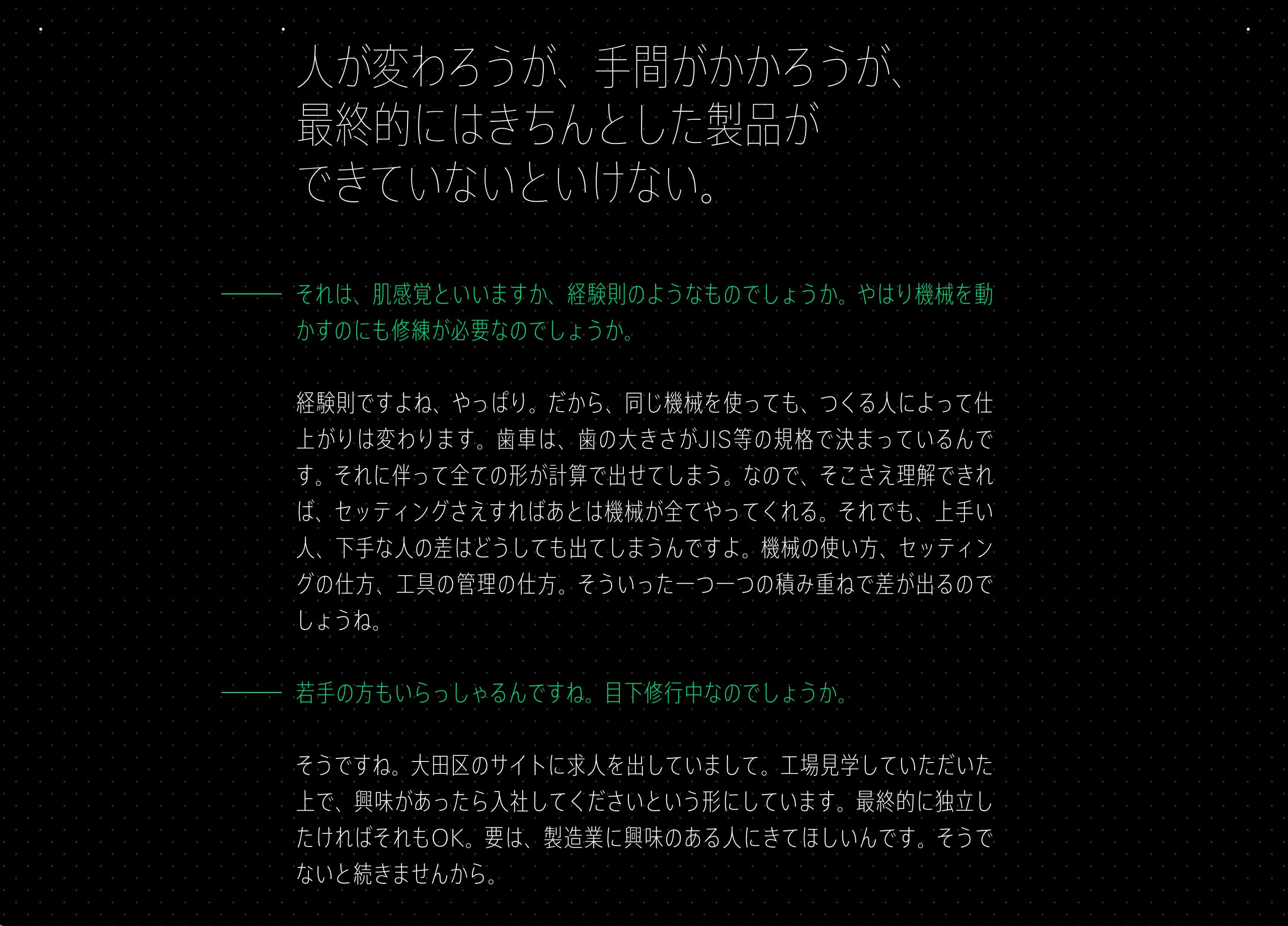
坂本氏は、大手企業のWebサイトの再構築も多く手がけています。最近の傾向として、PCからタブレット、スマートフォンまで、あらゆる画面サイズやさまざまな条件を満たす設計をする必要があるといいます。企業やブランドの持つ思想やトーンを体現することに加え、時代の流れに対しての不変性や耐久性、使いやすさ、速度などの面からも検証し、顧客企業の要望を実現します。ブランディングにおいて、文字とピクトグラムは非常に重要な要素のひとつになっています。デルトロでは、プロジェクトごとに、顧客企業やブランドに最適なピクトグラムをフルスクラッチするとともに、欧文フォントの開発も行なっています。
「AXIS Fontは、発表当時から知っていました。日本語サンセリフ体として、和欧混植への親和性が非常に高く、透明感があり、すっと雑音なく言葉が入ってくる、ニュートラルで品がある、とても希少なフォントだと思います。TP明朝やフィットフォントなど、これまでの既成概念を再定義し、『本来はこうあるべき』を実現する、タイププロジェクトによるドラスティックな挑戦にはいつも驚かされています。現在の日本語Webサイトは、インフラの関係もあり、デバイスフォントで表示される機会が圧倒的に多くなっています。文字も含めた本当の意味でのブランディングには、まだ課題があると感じていますが、プリントからWebサイトまでを統合的にブランディングされることが当たり前になる未来を、1日も早く見てみたいです。タイププロジェクトには、『AXIS Fontの持つモダンな印象』から『暖かさ・手触り・伝統あるトラディショナルな印象』へと多段モーフィングする、フィットフォント的アプローチの新機軸フォントの開発を陰ながら期待しています」